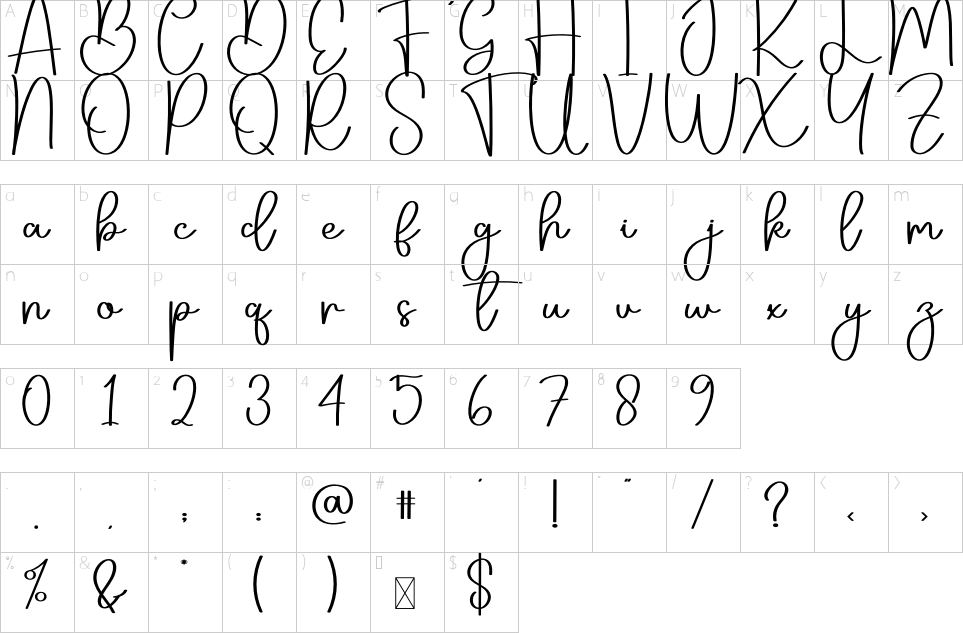
A fonte Monologue é um recurso gráfico gratuito disponível para download para usuários de Windows e Mac. Ela foi criada por scratchones e já foi baixada 334 vezes. Monologue é uma opção fácil de usar para adicionar personalidade a seus projetos digitais. Seja você um designer de logotipos, criador de sites ou mesmo um amante de design, Monologue pode oferecer a oportunidade de expressar sua criatividade de uma maneira única e moderna. Essa fonte traz alegria e um toque especial aos seus projetos, tornando-a uma escolha ótima para qualquer projeto de design. Descubra agora o que Monologue pode fazer para melhorar seu trabalho de design.